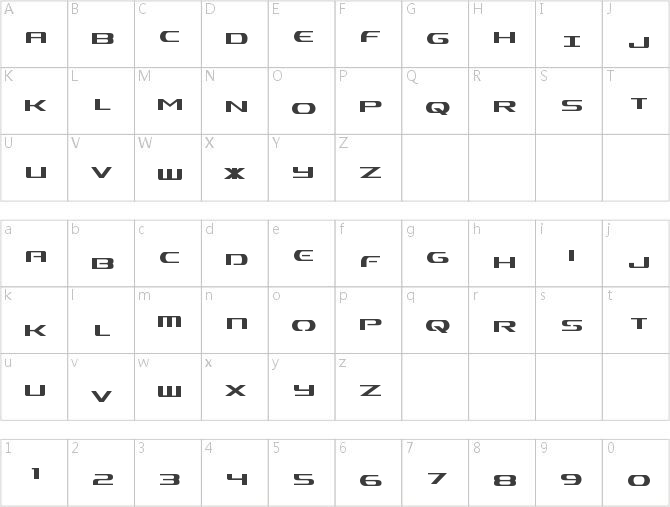
Alpha Men Condensed
Alpha Men Condensed介绍
Alpha Men Condensed字体字库是一款让人赏心悦目、百看不厌的英文字体,适合各类广告和产品包装设计应用,字体大小0.02MB,格式为ttf字体,上传用户是afig,作者/版权方为未知
Alpha Men Condensed效果图